コンニチハ。モジノスケデス。
イワカン ノ アル デダシ デ スミマセン。
読み飛ばさずに「ん?いつもとちがうぞ。」と思われた方、ありがとうございます。そして、失礼しました。
今日のお題は、「文字から伝わるニュアンスの幅」です。
日本語の文字である「ひらがな」と「カタカナ」や、漢字、アルファベットを例に挙げてお話ししたいと思います。
特に意味はないですが、景気づけに、けんしんフォントの「ひらがな」と「カタカナ」で表現してみましょう。
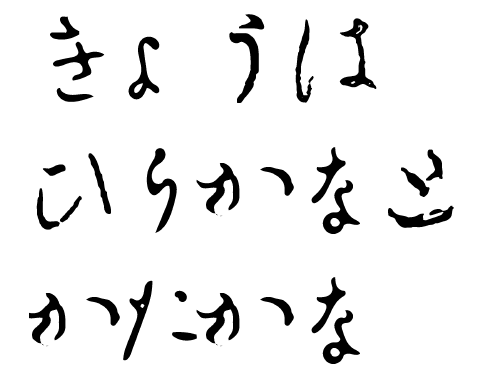
うーん。いつ見ても上杉謙信の文字は美しいですね。
みなさんはどちらがしっくりきますか。気分や好みに左右されそうですね。上杉謙信の「ひらがな」はもちろんのことですが、「カタカナ」にもなかなかの味があります。
フォントのいいところは、好きな人の字で自分の好きな言葉や文章を作れる点にあります。このブログの中でも、時々使っていこうと思います。
景気づけのつもりがちょっと脱線してしまいました。
それでは、「文字から伝わるニュアンス」の話に入っていきましょう
1 ニュートンとライプニッツ
このお題を考えるきっかけになったのは、次の本です。
著者の酒井先生はこんなご経歴です。
酒井先生の視点はとても刺激的で、私にとって新しい発想のタネになっています。
この本は7年前の2011年に出版されていますが、内容は古くありません。「電子書籍」と「紙の本」の比較など、たくさんの気づきをもたらす良著です。
内容に関する話題は別の記事で検討するとして、今回は96ページと97ページに出てきたキーワードを採り上げたいと思います。
「ニュートン」、「ライプニッツ」と言えば物理を学ぶときに必ず出てくる偉人の名前ですよね。
さすが、偉大な業績を上げた科学者だけあって、威厳のあるたたずまいです。いかにも厳しそうです。もし私たちが大学生だったとしたら、この人たちの講義に出席するためには、相当な覚悟をしておく必要がありそうです。出席したらしたで、難しい質問のときに、当てられそうです。
それではこの偉大な科学者たちの名前を「ひらがな」で表現するとどうなるでしょうか。見てみましょう。
![]()
にゅーとん
![]()
らいぷにっつ
どうですか? 急に親近感がわいてきませんか?
いかめしい風貌も「ギャグのための前振り」とさえ思えてきます。そこまでとは思わなくても、おやじギャグの1つや2つは言いそうな雰囲気に見えてきました。
「にゅーとん」と「らいぷにっつ」の講義なら、私でも気軽に立ち寄れそうな気がします。
実は、酒井先生の「脳を創る読書」のP96、P97で出てきた単語は、「にゅーとん」「らいぷにっつ」だったのです。なお、これらの単語が出てきた文脈が気になった方は本を買ってお読みください。
2 ウルトラマン80 と もじのすけ
その他にも例を挙げたいと思います。
私が子どもの頃のウルトラマンと言えば、ウルトラマンタロウ、ウルトラマンレオ。そして少し後に出てきた「ウルトラマン80」(ウルトラマンエイティ)です。
1980年の作品ということで、80と名づけられたのだと思われます。
私が親に買ってもらった児童向けのウルトラマンの本では、「ウルトラマン80」はこのようにふりがな表記されていました。
「うるとらまんえいてい」
これだと浮世絵に出てきそうな雰囲気です。江戸期の絵師や噺家のような雰囲気もあります。
明らかに「うるとらまんえいてい」は「ウルトラマン80」のイメージとは違っていて、子ども心に「ダサい」と感じていました。大人になった今なら、「出版する立場からすれば子どもが読めないと仕方ないし」と理解はできるのですが・・・。(でも今度は、「ウルトラマンでありながら、地球の暦の1つにすぎないグレゴリオ暦に名前を依存させるなんて」と思ってしまいますが。)
文字によって印象が変わる例を他にも挙げてみましょう。
「もじのすけ」だって印象が変わります。
モジノスケ
もじのすけ
文字之助
MOJINOSUKE
「モジノスケ」は、電化製品のイメージがわきます。「文字之助」は、からくり人形のイメージでしょうか。「MOJINOSUKE」は無印良品のレトルトパックのスープみたいです。
「よろしく」だって違ってきます。
よろしく
宜しく
ヨロシク
夜露四苦
YOROSHIKU
どうでしょうか。それぞれ印象が違いませんか。「夜露四苦」をみると漢字は表音文字ではなく、表意文字だなあと実感します。
3 違和感の正体
私が「にゅーとん」「らいぷにっつ」に親近感をいだき、「うるとらまんえいてい」をダサいと感じてしまったのは、なぜでしょうか。
もう少し一般化すると、ひらがな、カタカナ、漢字、アルファベットで印象が違うのはどうしてでしょうか。
3-1 漢字
まず、漢字は印象が変わるのは無理もないと思います。漢字は表意文字であり、一文字一文字にニュアンスがありますから。
夜露四苦は、「夜の露」というはかなさを感じさせますし、「四苦」は「四苦八苦」という苦しみの一部であることを感じさせます。単なる音の「よろしく」とは違いそうです。
3-2 アルファベット
アルファベットも印象が変わる理由は思いつきます。アルファベットは日本語の表記として一般に使われた文字ではなく、英語などの外国語の文字として使われています。「MOJINOSUKE」と書くと、自然に日本以外のテイストが入ってくることになります。
3-3 ひらがなとカタカナ
にわかに理由が思いつかないのが、ひらがなとカタカナから伝わるニュアンスの違いです。
「にゅーとん」「らいぷにっつ」「うるとらまんえいてい」
どれも日本語の表記として一般に使われた文字であり、表音文字であることも共通です。ニュアンスの違いは、いったいどこから来るのでしょうか。
あれこれ考えたのですが、理由は2つありそうです。
1つは、「文字の形」です。
ひらがなの場合、文字の線は一画でも揺らいだり何度も曲線が出てきます。
単純な直線は無いといってもいいくらい少ないです。そして読む人にやわらかい印象を与えます。
「にゅーとん」「らいぷにっつ」の印象の変化はここからくるでしょう。
![]()
にゅーとん らいぷにっつ
他方、カタカナの場合は、一画の中の揺らぎは少なく直線が多めになります。論理的という印象や、無駄を排した堅い印象を与えます。
![]()
このように「ひらがな」と「カタカナ」の文字の形自体から、読む人に与える印象が変わってきます。
もう1つの理由は、私たちの中にある「通常の用法という先入観」です。
普段私たちが文章を読むときは、「ここは『ひらがな』、ここは『カタカナ』」と通常の用法を予測しながら読んでいます。この予測が外れると急に違和感をいだき、特別な意味があるのではないかと疑います。
ソウデショウ?
その他にも「ヒラガナ」と「かたかな」と書くと違和感が出てきませんか?
![]()
にゅーとん らいぷにっつ
この2つから受ける違和感は、外国人の名前にアルファベットでも「カタカナ」でもなく、「ひらがな」を使うところからも来るのだと思います。
日本人の名前(たとえば「松岡修造」)のところにカタカナ(「マツオカシュウゾウ」)を使ってみましょう。急に「ハーフの人かな?」とか思えてきます。
「文字の形」と「通常の用法という先入観」。
この2つの理由から、「ひらがな」と「カタカナ」のニュアンスの違いが出てくるように思います。
4 次回の予告
今回は書体(フォント)のデザインの話ではなく、文字の種類(「ひらがな」「カタカナ」「漢字」「アルファベット」)から来るニュアンスの違いのお話でした。
特に「ひらがな」も「カタカナ」のように、「同じ日本語の表音文字なのに、種類が違うだけで与える印象が変わる」という事実は、私には不思議な現象のように思えて仕方がありません。
「ひらがな」や「カタカナ」の印象を変化させる、私たちの「通常の用法という先入観」については、次回も検討したいと思います。
私たちがいかに先入観を持って文字を読んでいるか、というお話です。
キョウ ハ コノヘン ニ シテオキマショウ。
オツカレサマデシタ。